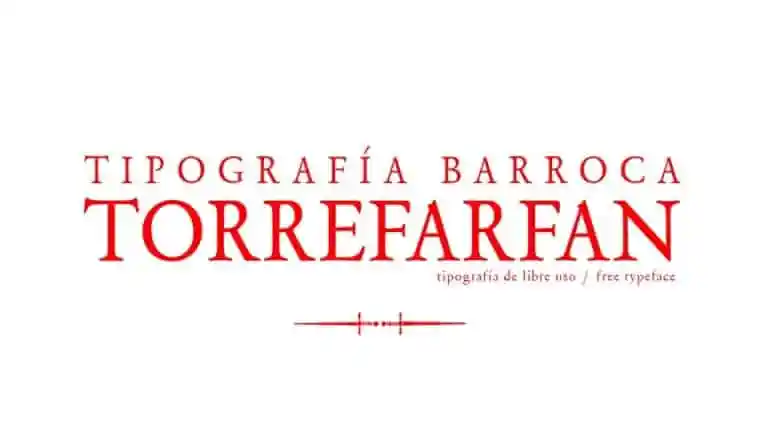
TorreFarfan Serif é uma fonte serif que traz alternativas estilizadas para projetos mais elegantes. Com influências arquitetônicas marcantes nos caracteres, a TorreFarfan possui uma arquitetura de formas tipográficas que se encaixa bem em um momento de transição na história da tipografia. Percebemos características clássicas da morfologia romana tradicional, mas também elementos evolutivos que a aproximam do moderno modelo romano. Algumas das suas semelhanças com as fontes do tipo Garaldas são notáveis, remetendo às típicas fontes de meados do século passado e criadas pelo Francesco Griffo para Aldo Manucio em 1495. Nesse contexto histórico da tipografia, a TorreFarfan Serif é uma ótima escolha para quem procura um equilíbrio entre o clássico e o moderno na sua próxima criação gráfica.